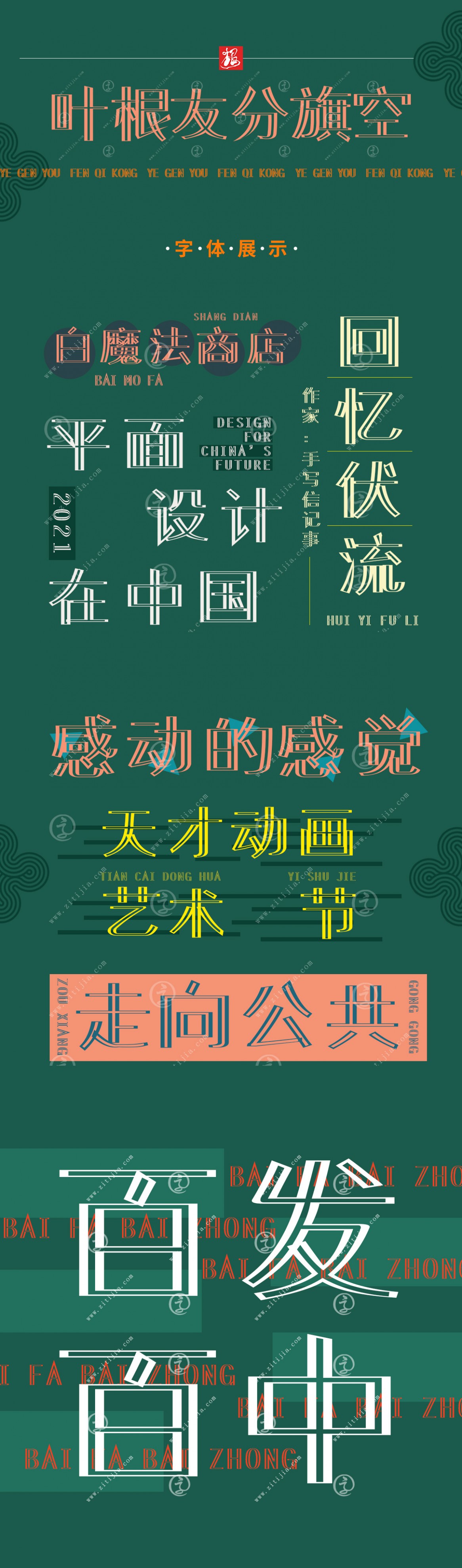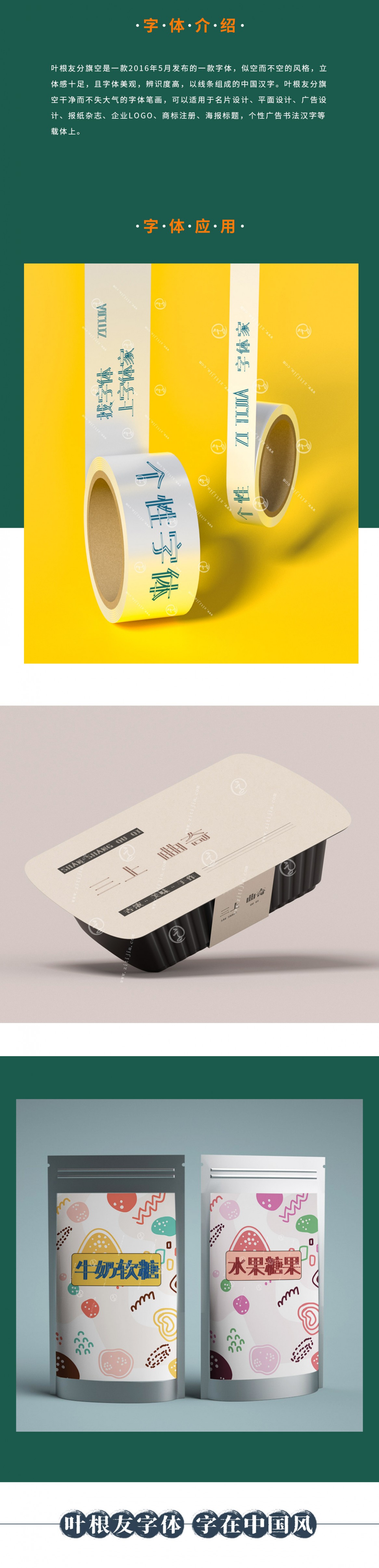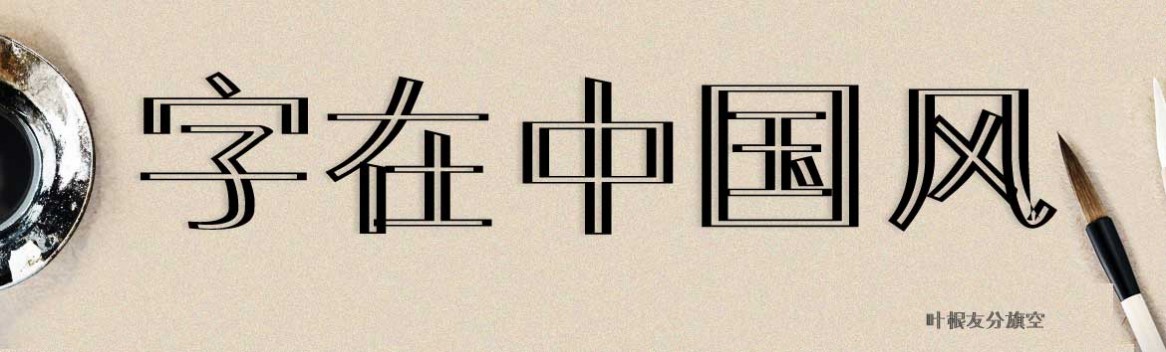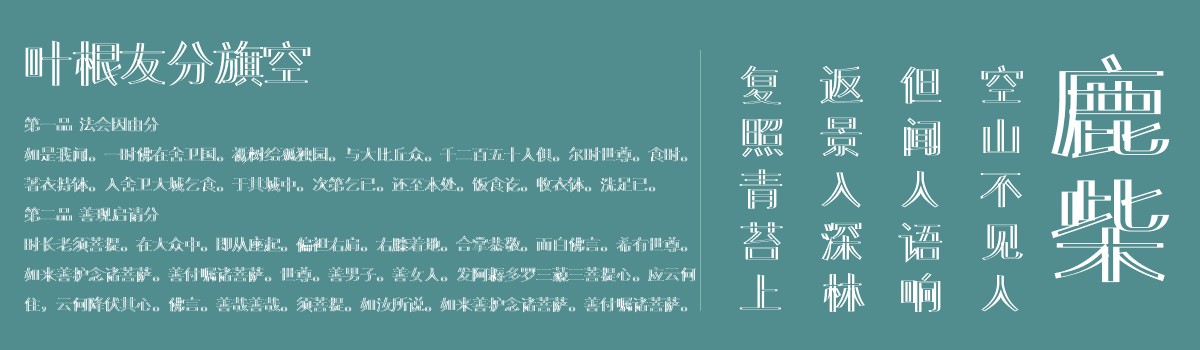
叶根友分旗空
创作年代:2016年
字体字数:6763个中文汉字以及其他英文字母和阿拉伯数字
字体介绍
叶根友分旗空是一款2016年5月新发布的一款字体,似空而不空的风格,以线条组成的中国汉字,对现在黑体看多了的电脑用户来说是一种新鲜的感觉,我们可以用更新的思维来探索中国汉字字体的发展,而不局限横竖撇捺的方正平划,叶根友分旗空适用于各类海报标题,个性广告书法汉字等载体上,具体怎么用还是看各位看官心中美感了。
字体应用